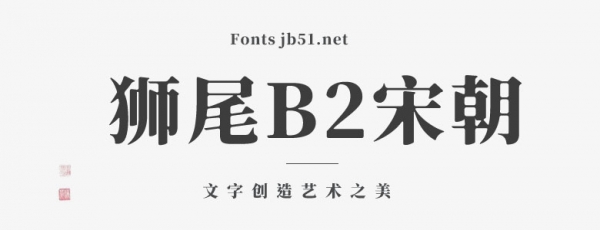
獅尾B2宋朝字體(Swei B2 Serif CJKtc)是中國(guó)臺(tái)灣的MAX基于思源宋體創(chuàng)作的一款字體,將轉(zhuǎn)角的三角形通過(guò)程序自動(dòng)轉(zhuǎn)成半圓形改造,看起來(lái)好像墨暈或是稍微過(guò)曝的效果。支持簡(jiǎn)體中文、繁體中文、韓文與日文;歡迎大家自由應(yīng)用、自由優(yōu)化、自由改作!